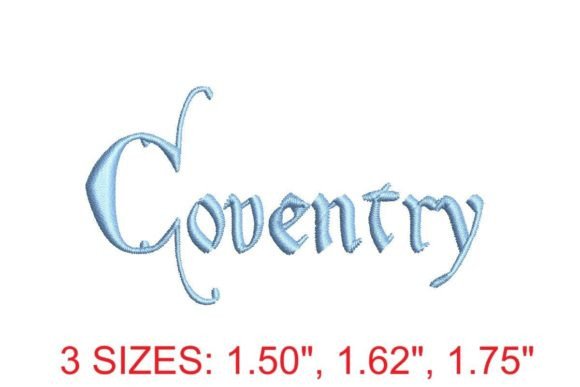
Coventry Embroidery Font
Việc tìm kiếm các thành phần thiết kế phù hợp có thể là một thách thức, nhưng Coventry Embroidery Font cung cấp một bộ sưu tập đặc biệt giúp nâng tầm công việc của bạn ngay lập tức.